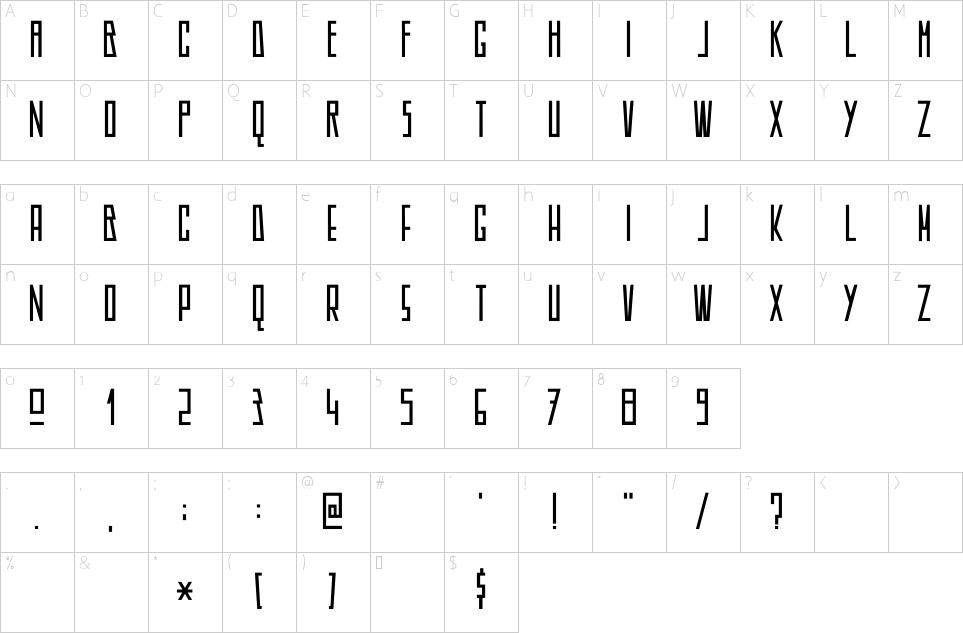
Descubra a DK Americain Font, uma elegante e versátil opção para seu próximo projeto gráfico. Essa fonte foi criada por Hanoded especialmente para aqueles que procuram um estilo americano clássico e contemporâneo. Com um design minimalista mas poderoso, a DK Americain é perfeita para criar headlines ou subtítulos em qualquer aplicativo de design que você use – seja no Mac ou Windows. Seja você um designer profissional ou iniciante, essa fonte gratuita oferece uma solução confiável e versátil. Até agora, mais de 2.939 pessoas já desfrutaram da DK Americain Font, o que prova a sua popularidade e eficácia. Caso deseje incorporar essa estética única em seus projetos, é só baixar e começar a experimentar.